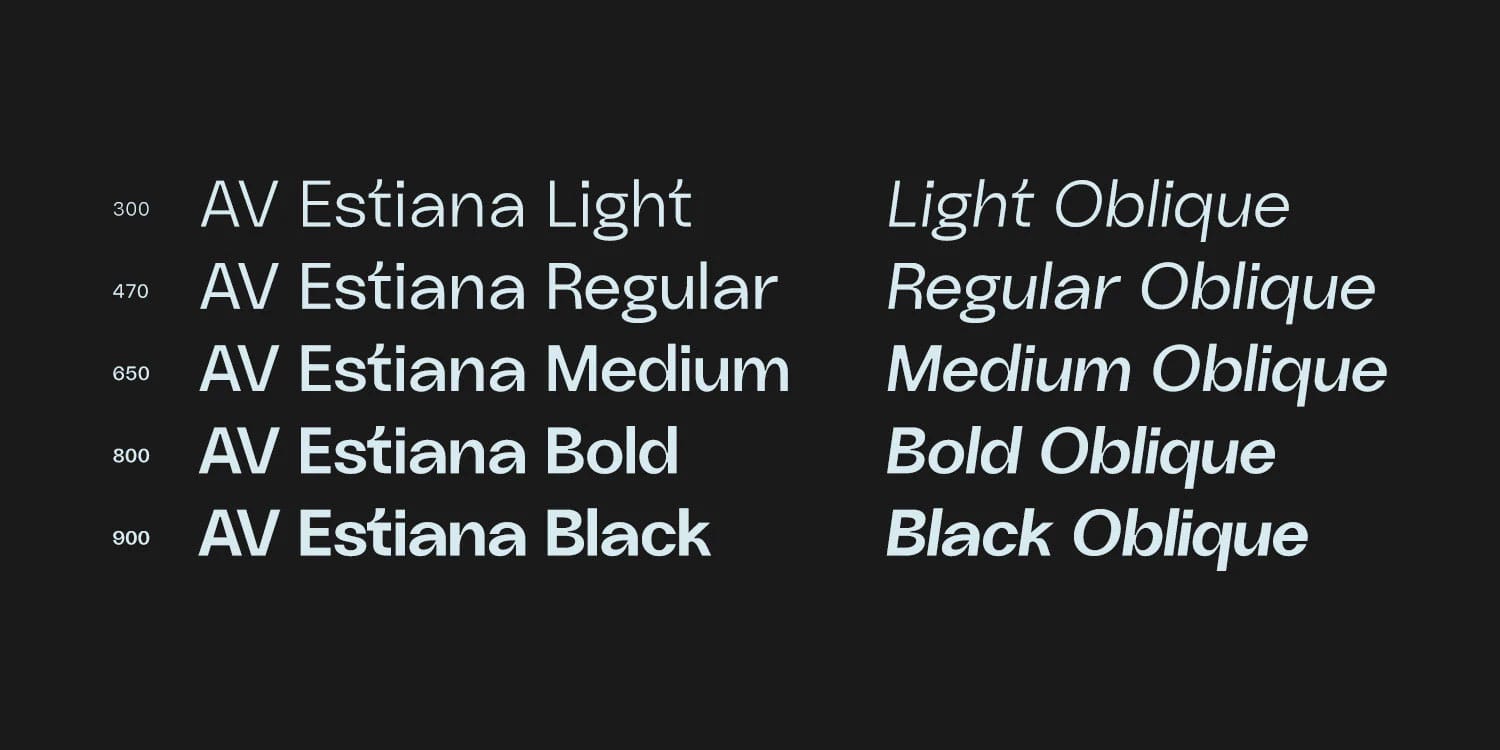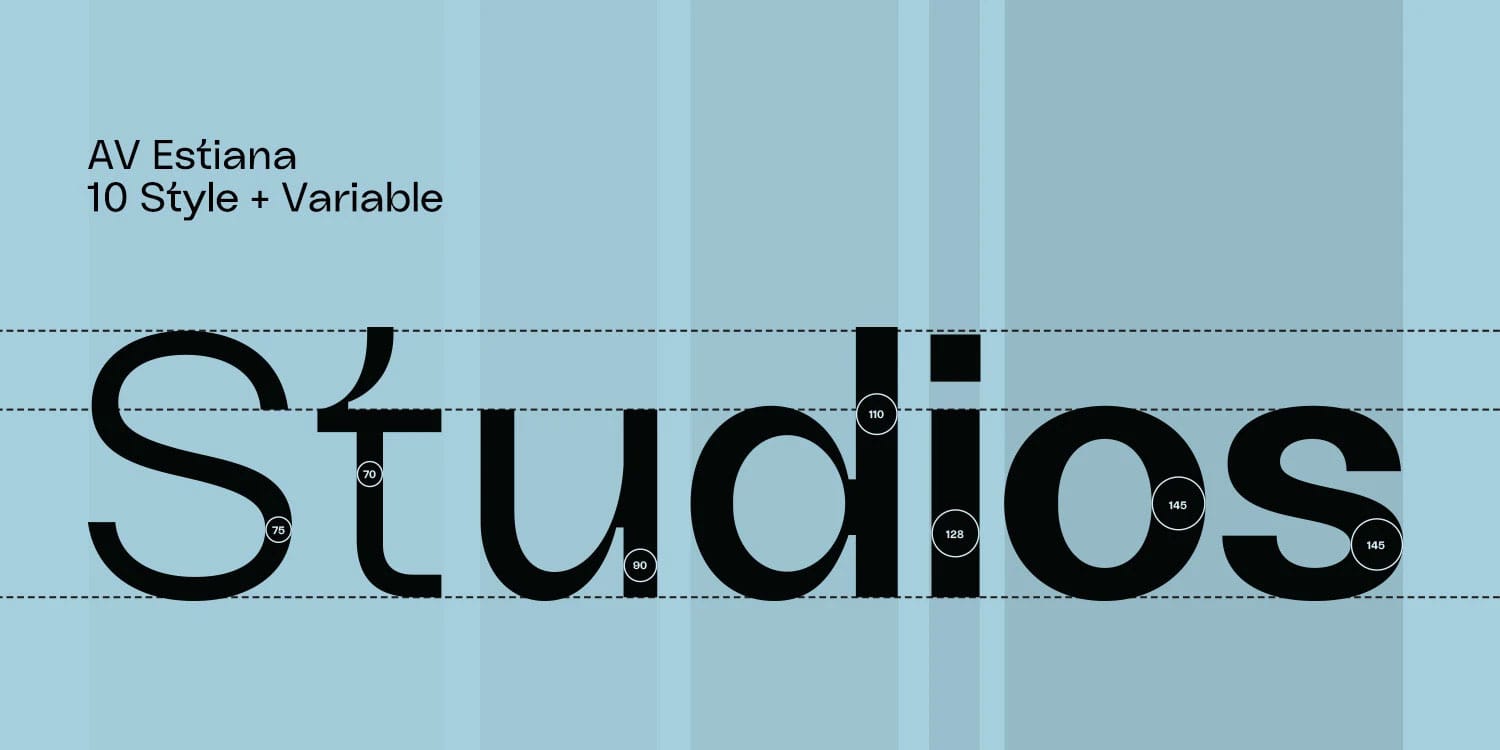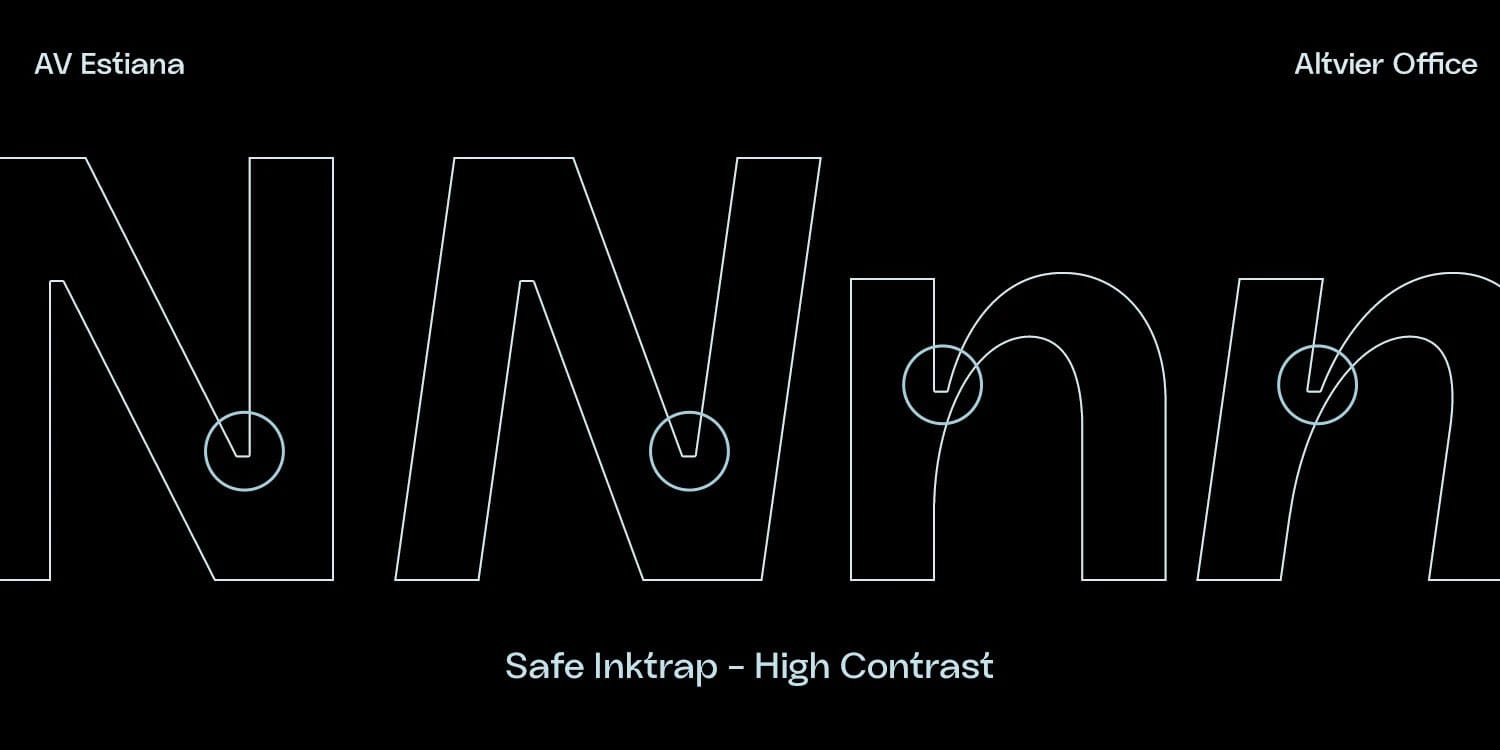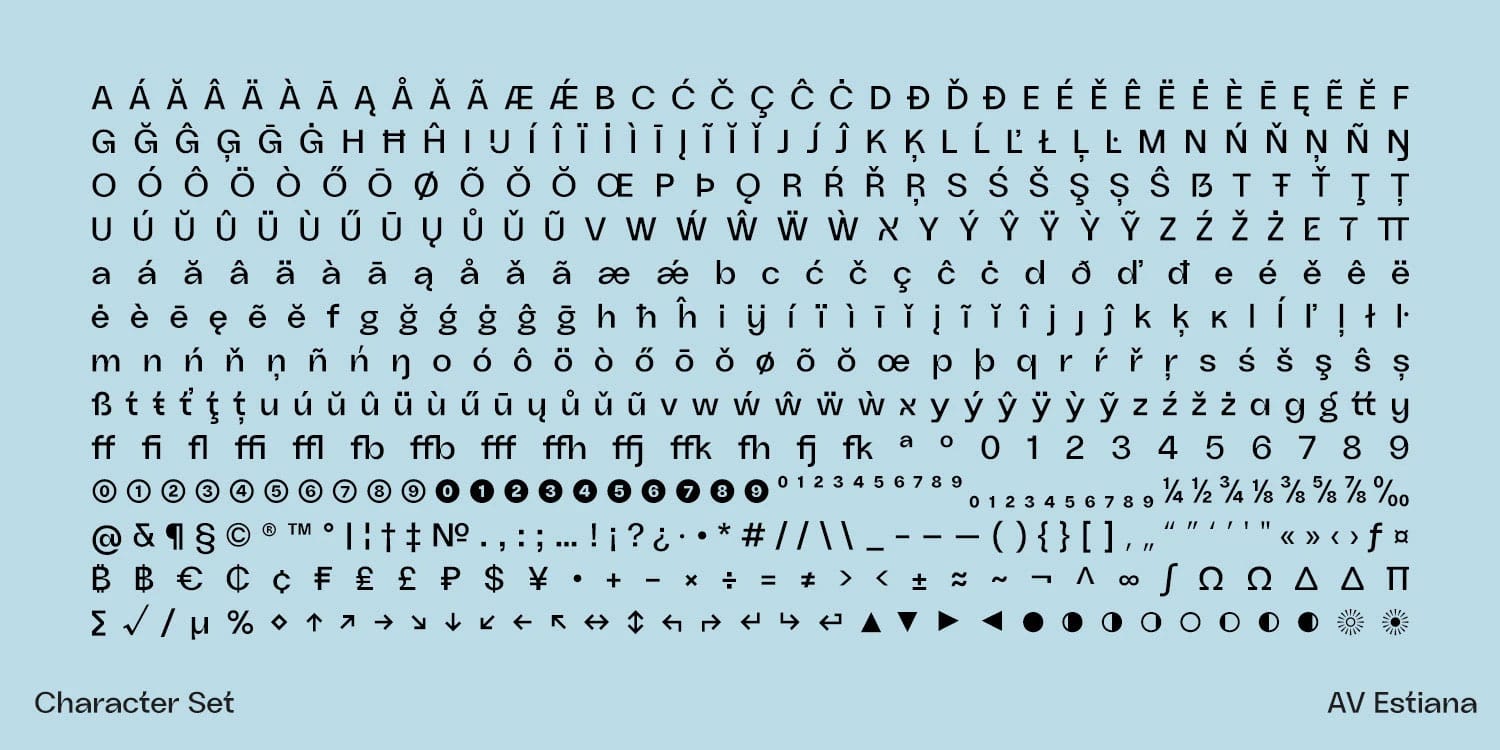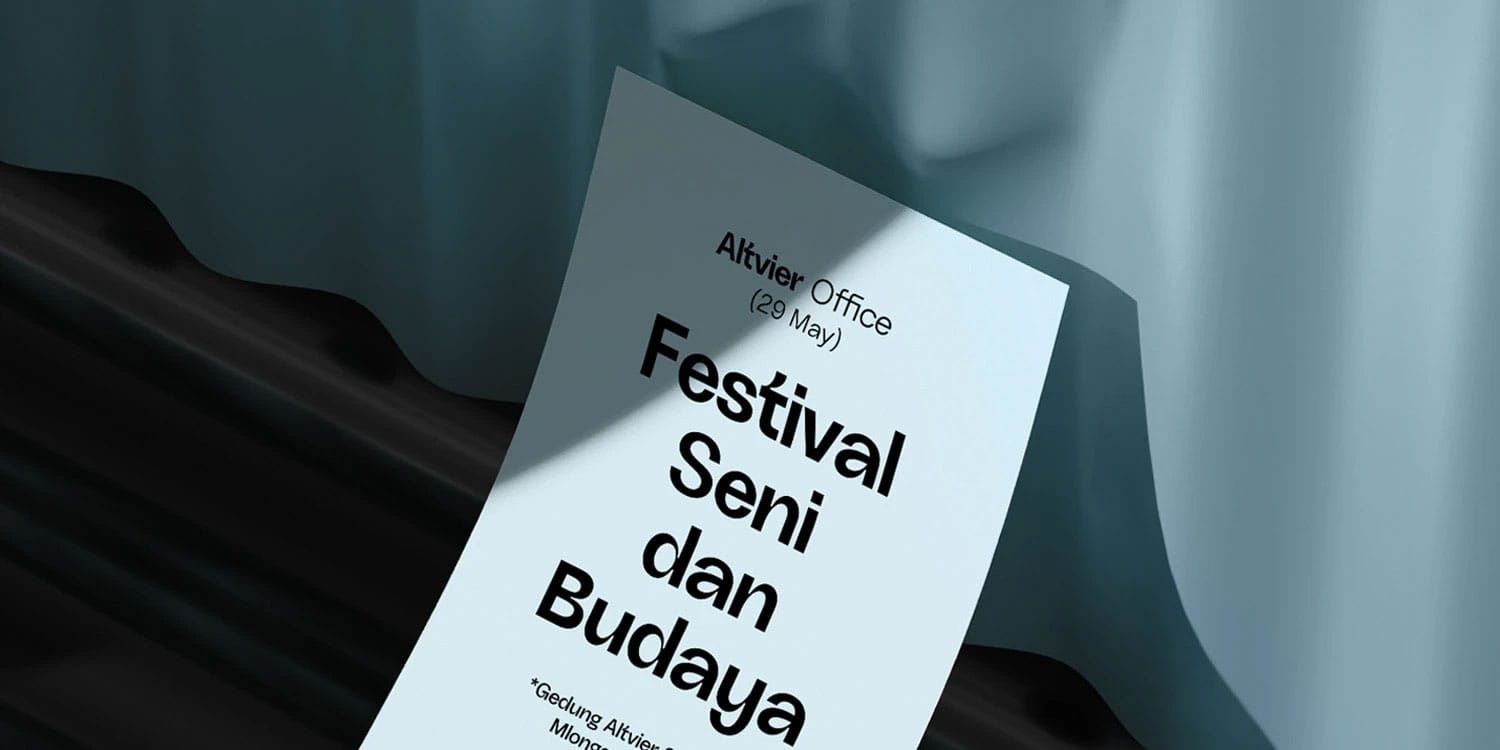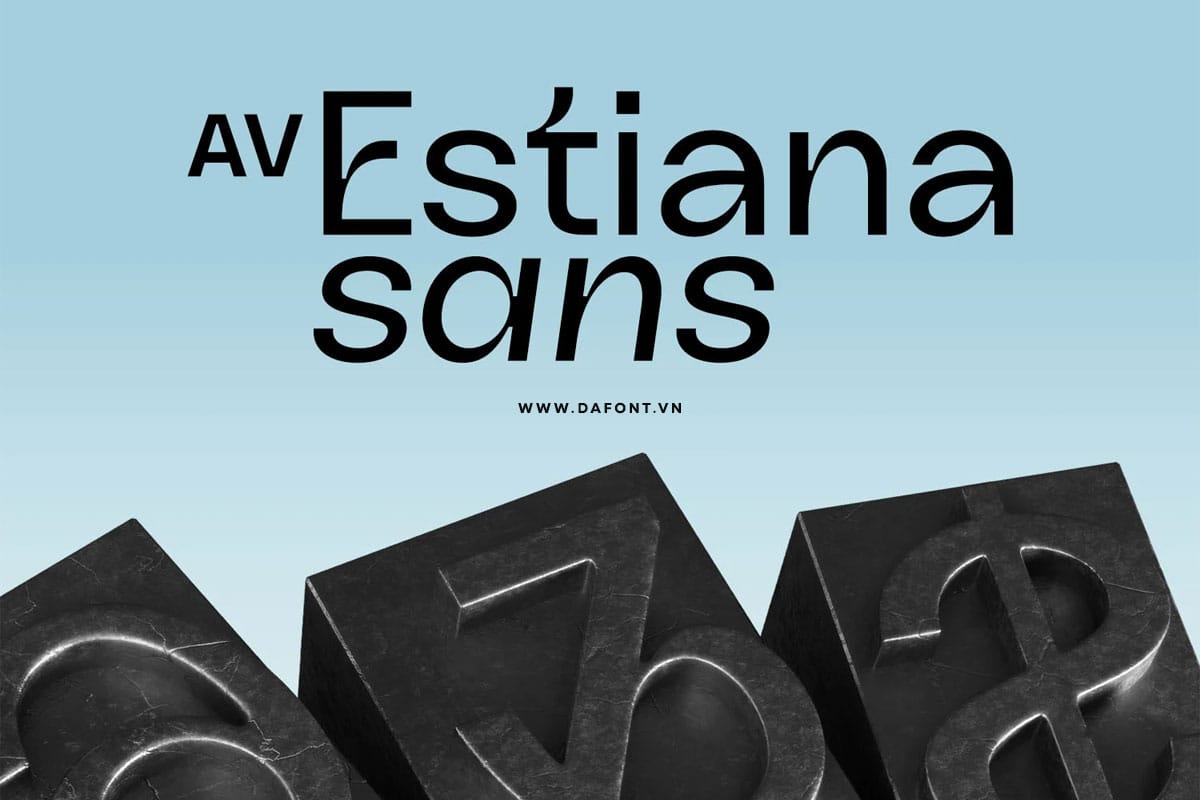
Nếu bạn từng gặp tình trạng layout bị xô lệch khi đổi chữ từ Regular sang Bold (đặc biệt trong UI/UX, dashboard, web), thì AV Estiana Font là một lựa chọn đáng cân nhắc. Điểm “ăn tiền” của font này nằm ở thiết kế uniwidth: các ký tự được tối ưu để giữ độ rộng ổn định giữa các weight, nhờ vậy bạn thay đổi độ đậm nhạt mà không làm vỡ bố cục.
Đây là kiểu chữ phù hợp cho nhiều ngữ cảnh: từ UI/UX, branding, poster, đến editorial khi bạn muốn một cảm giác sạch sẽ, dễ đọc và có tính hệ thống.
Đặc điểm nổi bật
Đặc điểm thiết kế quan trọng nhất: Uniwidth
Điểm đặc biệt nhất của AV Estiana chính là tính chất Uniwidth (độ rộng đồng nhất). Điều này có nghĩa là:
- Dù bạn thay đổi trọng lượng font (từ Thin sang Bold), độ rộng tổng thể của văn bản vẫn không thay đổi.
- Các ký tự ở các biến thể khác nhau chiếm cùng một khoảng không gian ngang. Điều này cực kỳ hữu ích trong thiết kế giao diện (UI/UX) hoặc layout báo chí, vì bạn có thể chuyển đổi độ đậm nhạt của chữ mà không làm nhảy dòng hay phá vỡ bố cục thiết kế đã định sẵn.
Phong cách thẩm mỹ
- Minimalist (Tối giản): Font có đường nét sạch sẽ, hiện đại và trung tính.
- Hình học (Geometric): Cấu trúc chữ được xây dựng dựa trên các hình khối cơ bản, mang lại cảm giác chính xác và chuyên nghiệp.
- Tính linh hoạt: Phù hợp cho cả tiêu đề (headlines) lẫn văn bản ngắn trong UI, hệ thống lưới (grid-based layout) và thiết kế đồ họa thương hiệu.
Thông số kỹ thuật
- Định dạng: 10 style (5 weight + bản nghiêng/oblique tương ứng) và có thêm 1 file Variable.
- Phân loại: Sans Serif / Display.
- Designer: Ahmad Nur Alfian (Alpha Visual).
- Năm phát hành: Khoảng năm 2025 (nằm trong các bộ sưu tập font mới tiêu biểu của năm).
AV Estiana là một bộ font sans serif hiện đại, nổi bật nhờ đặc tính uniwidth giúp giữ bố cục ổn định khi thay đổi weight. Nếu bạn làm UI/UX, design system, hoặc branding tối giản và muốn một font sạch – gọn – dễ triển khai, AV Estiana là lựa chọn đáng thử.
AV Estiana Font Family Preview